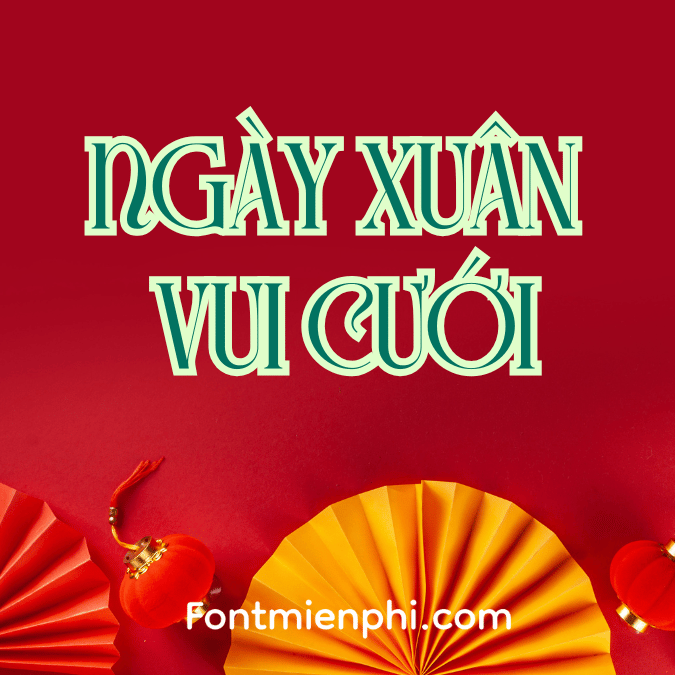
Font Việt hóa 1FTV VIP Glamora ,Font tết
Mô Tả về Font Việt Hóa 1FTV VIP Glamora và Font Tết
Font Việt hóa 1FTV VIP Glamora là một kiểu chữ độc đáo, mang đến sự sang trọng và hiện đại. Font này thường được sử dụng trong các thiết kế đồ họa, bao gồm bìa sách, poster, và các sản phẩm truyền thông. Với những đường nét mềm mại và tinh tế, Glamora không chỉ tạo cảm giác thoải mái mà còn thu hút người nhìn. Font này rất phù hợp cho các sự kiện lớn như đám cưới, tiệc tùng hay các buổi lễ kỷ niệm.
Font Tết là kiểu chữ thường được sử dụng trong các thiết kế liên quan đến Tết Nguyên Đán. Với những họa tiết và đường nét mang đậm bản sắc văn hóa Việt Nam, Font Tết thường thể hiện những hình ảnh vui tươi, phấn khởi liên quan đến mùa xuân như hoa mai, hoa đào, hay những câu chúc tốt lành. Font này không chỉ giúp tạo ra không khí lễ hội mà còn gợi nhớ đến những truyền thống tốt đẹp của dân tộc.
Cả hai font này đều mang lại sự phong phú trong thiết kế và có thể kết hợp với nhiều yếu tố khác nhau để tạo nên những tác phẩm ấn tượng.